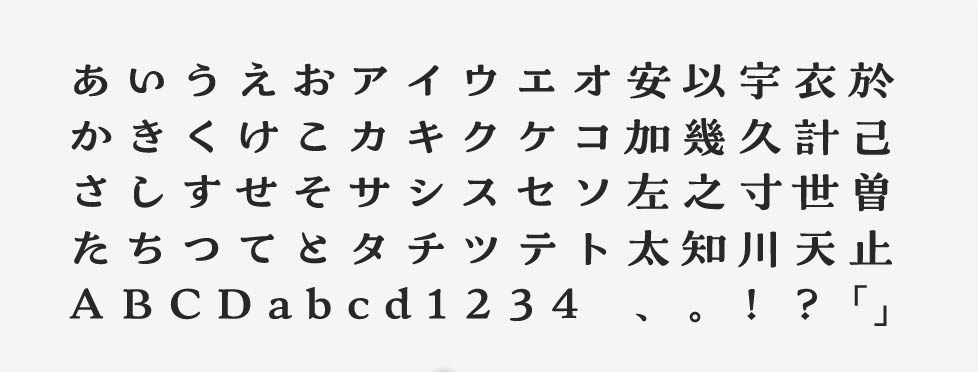
「ちさき」について
ちさきは、2022年の新書体としてリリースされました。書き文字や金属活字の要素が取り入れられたデザイン書体で、古風で可愛らしい明朝体風のフォントに仕上げられています。横長の平体ぎみに設計されていることも特徴で、文字列を組むとその個性がより際立つ設計です。
「ちさき」の特徴
ちさきの文字では、漢字の筆おさえやかなの筆脈といった筆のニュアンスに、デフォルメされたエレメントが組み合わせられています。伝統的な要素が見られるものの、現代的な表現にも十分に使えるフォントです。もちろん、古風な側面を生かしてレトロな演出にも役立ちます。
独特な雰囲気のちさきは、柔らかなイメージや上品な印象のデザインにもマッチしやすいでしょう。見出しやキャッチコピーなどで、ほかのデザイン要素との組み合わせ次第でさまざまな表情を見せることができます。
作例で活用したちさきは、ひらがなのデザインが素晴らしいフォントです。可読性が高く、縦組みと横組みのどちらでも全く問題なく使えます。「和」なデザインにおいて特に魅力を発揮しますが、比較的に幅広いジャンルで使えるのではないでしょうか。